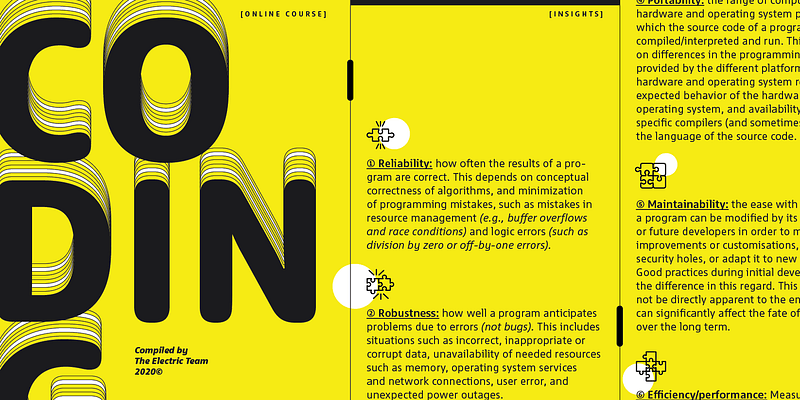
La struttura e l’aspetto di base di Dico (parola latina che significa parlare, conversare, discutere) hanno proporzioni compatte e forme delle lettere aperte ma sobrie che guadagnano in cordialità e calore se accompagnate dal loro corsivo più oscillante. Gli stili di scrittura a spaziatura fissa, vagamente basati sulla scrittura corinzia per IBM Selectric, possono donare una direzione ancora più piacevole. Lo spessore può sembrare piccolo rispetto ad altre grandi famiglie di font, ma Dico compensa ampiamente con altre variazioni corrispondenti sul tema. Accanto al Sans puoi scegliere tra Slab-serif, Dico Soft arrotondato, Sans e Slab a spaziatura fissa, due varianti di Code e Dico Typewriter contenenti versioni “grezze” di Dico Mono Sans, Mono Slab e Mono Script. 45 font in totale.